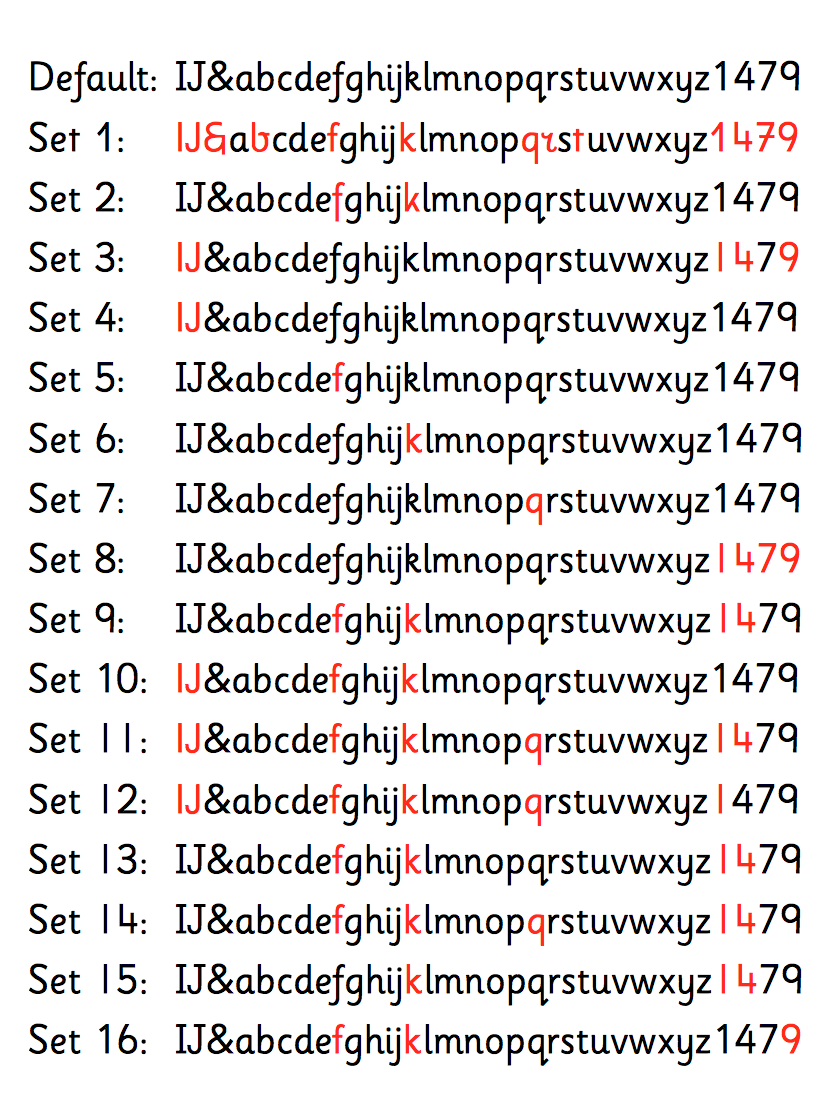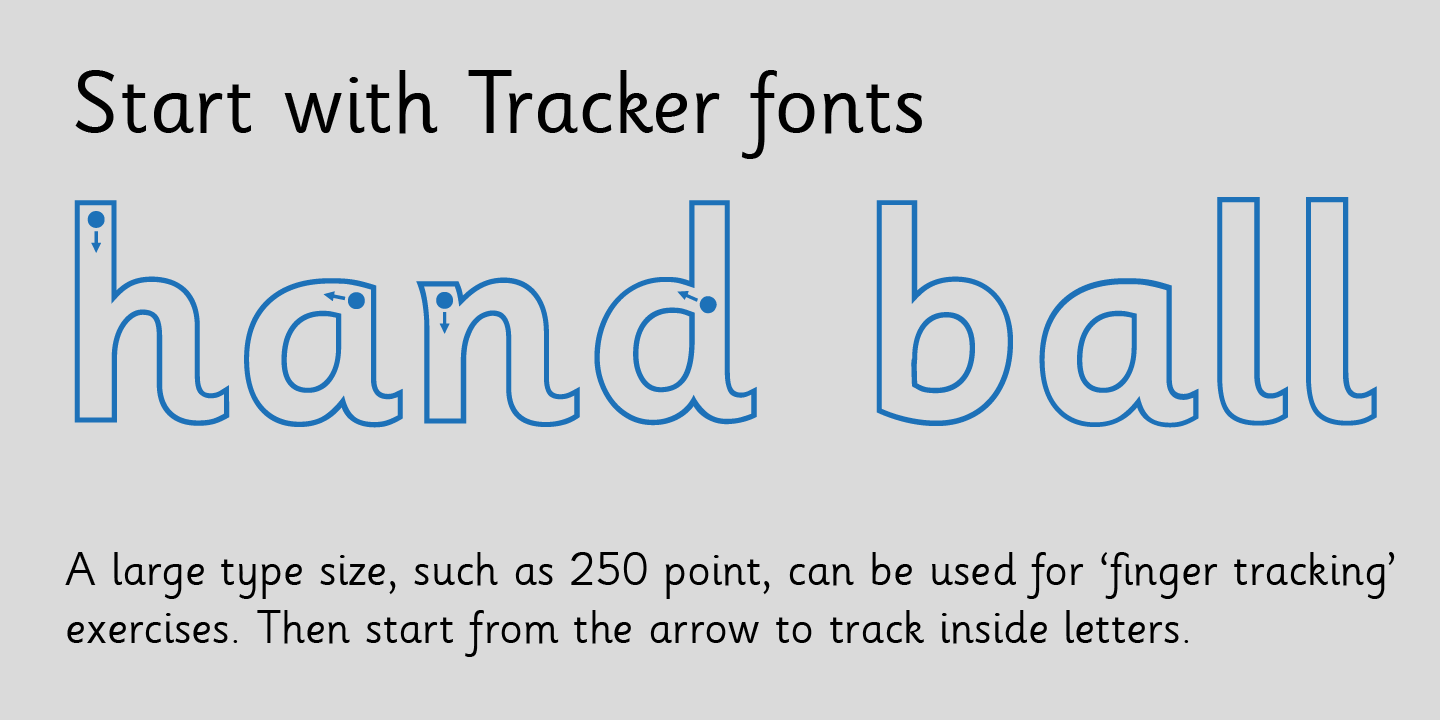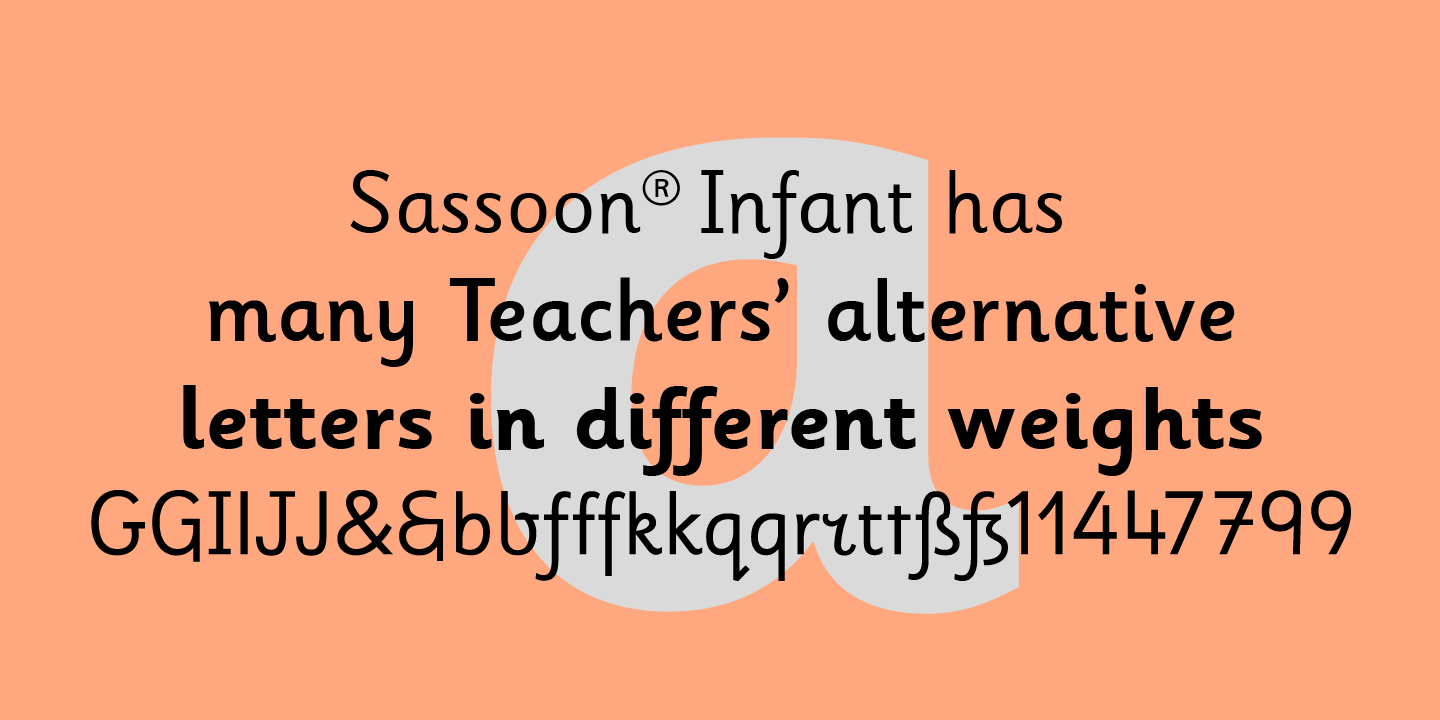
- 1995
- sans
- Antiqua humanistisch
Nach dem Stil von Schulbuch-Schriftarten des frühen zwanzigsten Jahrhunderts begann Rosemary Sassoon 1995 mit dem Entwurf der Sassoon-Schriftfamilie (Primary, Infant, Sans, Book). Charakteristisch ist die Harmonie zwischen dem Raum innerhalb und außerhalb der Buchstaben.
Inzwischen entstanden mehrere Versionen:
Sassoon Infant:
Normalversion zum Schriftsatz -
Sassoon Infant Line:
Normalversion mit Grundlinie -
Sassoon Infant Tracker:
Outline-Variante mit und ohne Richtungspfeil zum Nachschreiben -
Sassoon Infant Dot:
Punktversion mit und ohne Richtungspfeil zur Erläuterung der Strichansätze (dicker Punkt) - Sassoon Infant Pro: Normalversion mit erweiterter Sprachunterstützung, unter anderem polytonischem Griechisch
Merkmale der Sassoon Infant:
- Drei Strichstärken (regular, medium, bold)
- 16 Stylistic Sets für entsprechend gewählte Lese- und Handschrift-Regularien